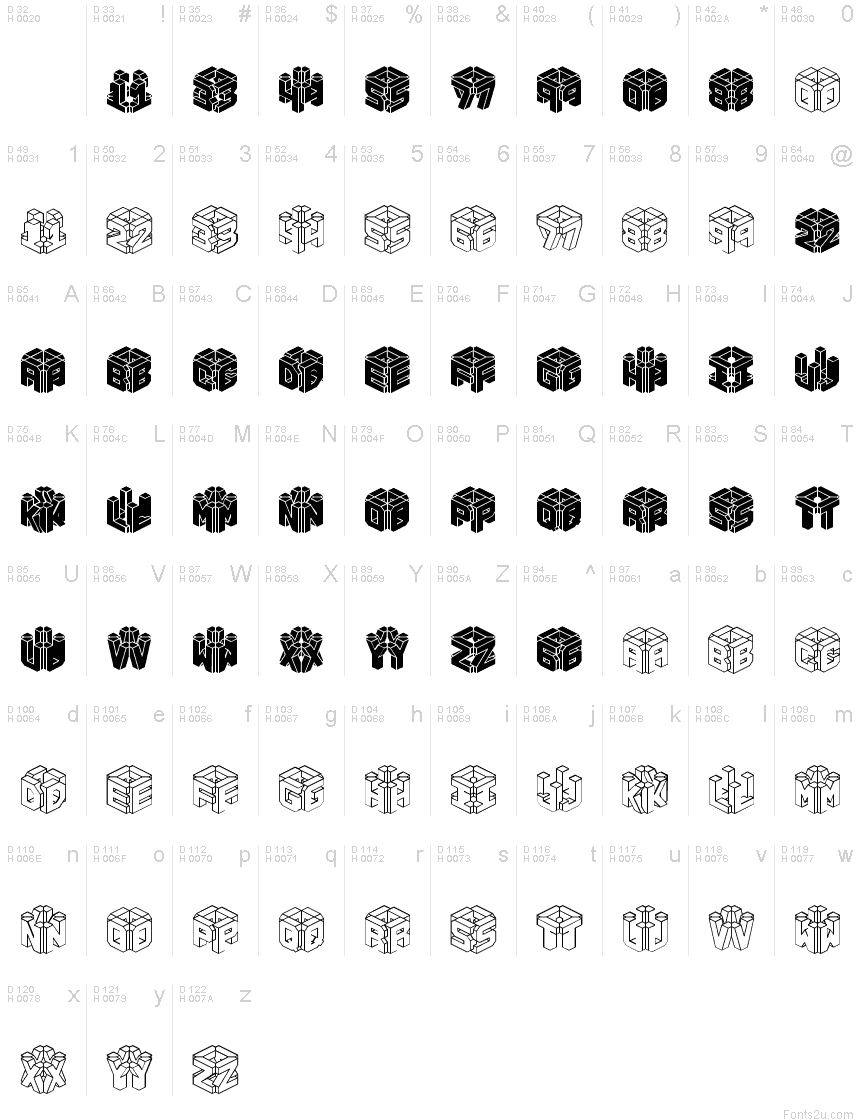
3d Let di ÆNIGMA FONTS è un font 3D display gratuito che trasforma ogni parola in un complesso incastro di blocchi isometrici. Ogni lettera sembra un piccolo rompicapo architettonico, con facce nere audaci, linee bianche interne nitide e angoli precisi che si incastrano come in un set di costruzioni modulare. Il risultato è un lettering denso e geometrico che appare come un labirinto da lontano e un disegno tecnico da vicino.
Grazie a 3d Let, i titoli acquistano immediatamente una presenza dimensionale massiccia impossibile da ignorare. Questo font gratuito è perfetto per titoli di giochi, poster sci-fi, volantini di eventi tecnologici, grafiche per serate underground, adesivi e logotipi audaci che richiedono un tocco meccanico e costruito. Usalo in dimensioni grandi per mantenere le linee interne definite e abbinalo a un sans serif pulito e neutro per il testo principale, lasciando che siano le forme cubiche a fare la parte del leone.